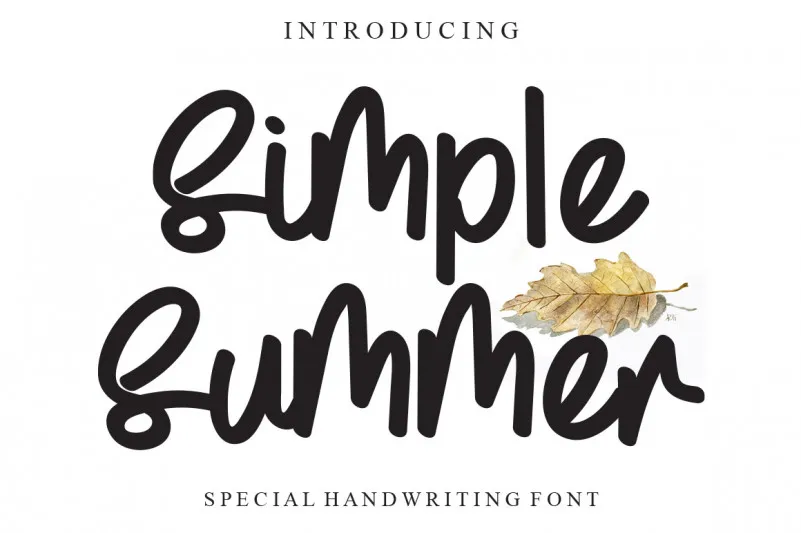
Simple Summer Font – Download Grátis
A fonte Simple Summer é uma seleção única para aqueles que desejam adicionar um toque fresco a suas criações digitais. Este design handwritten oferece uma sensação descontraída e animada, perfeito para personalizar cartões de natal, notas pessoais, logotipos ou qualquer projeto em que deseje transmitir uma mensagem leve e desconcertantemente amigável. Ideal tanto para aqueles que buscam simplicidade quanto para aqueles que valorizam um ar romântico, a Simple Summer é uma escolha perfeita para qualquer designer de recursos gráficos procurando por uma fonte versátil e encantadora para o seu próximo trabalho. Através do levincreative, você pode adicionar uma pitada divertida ao seu design sem sair da sua zona de conforto digital.